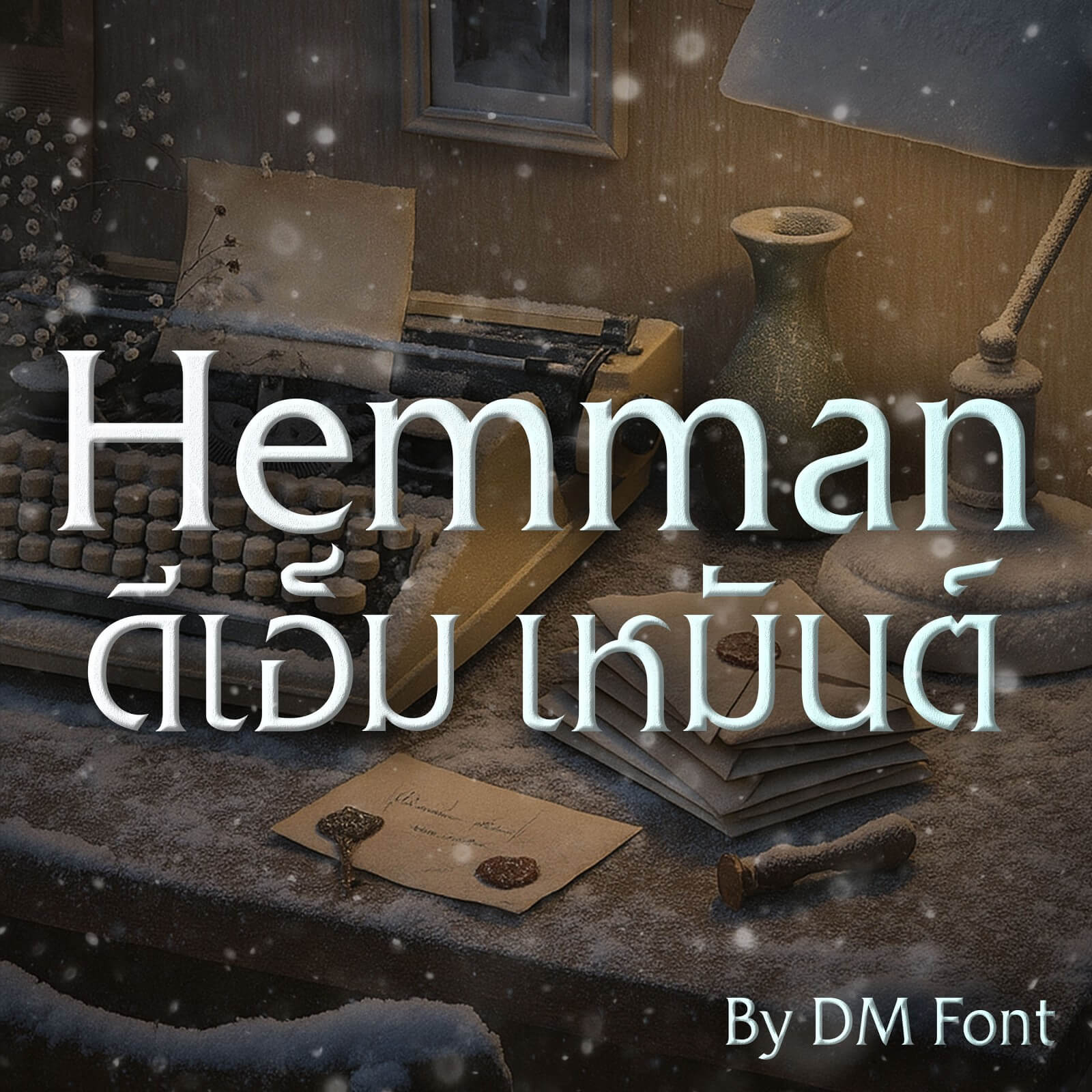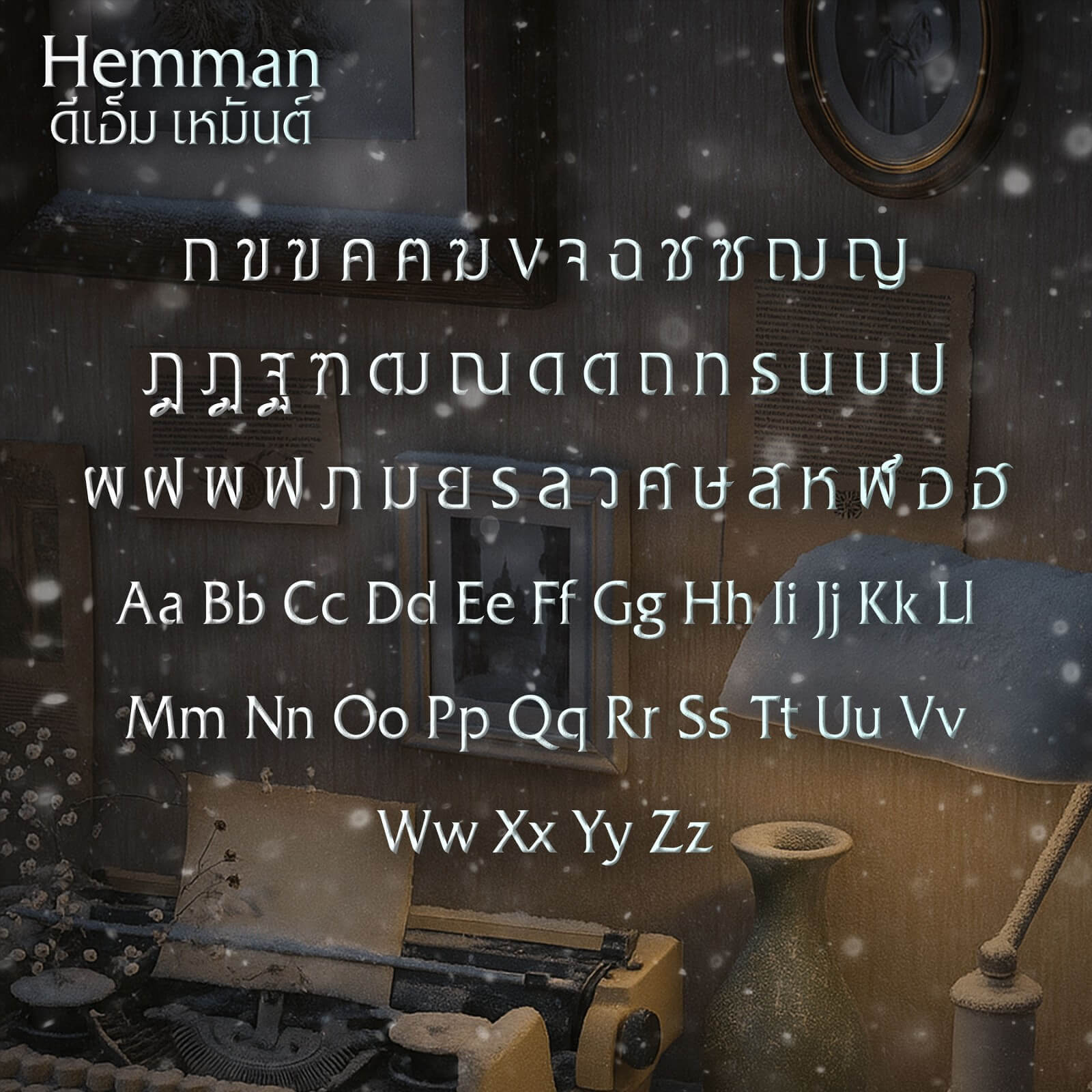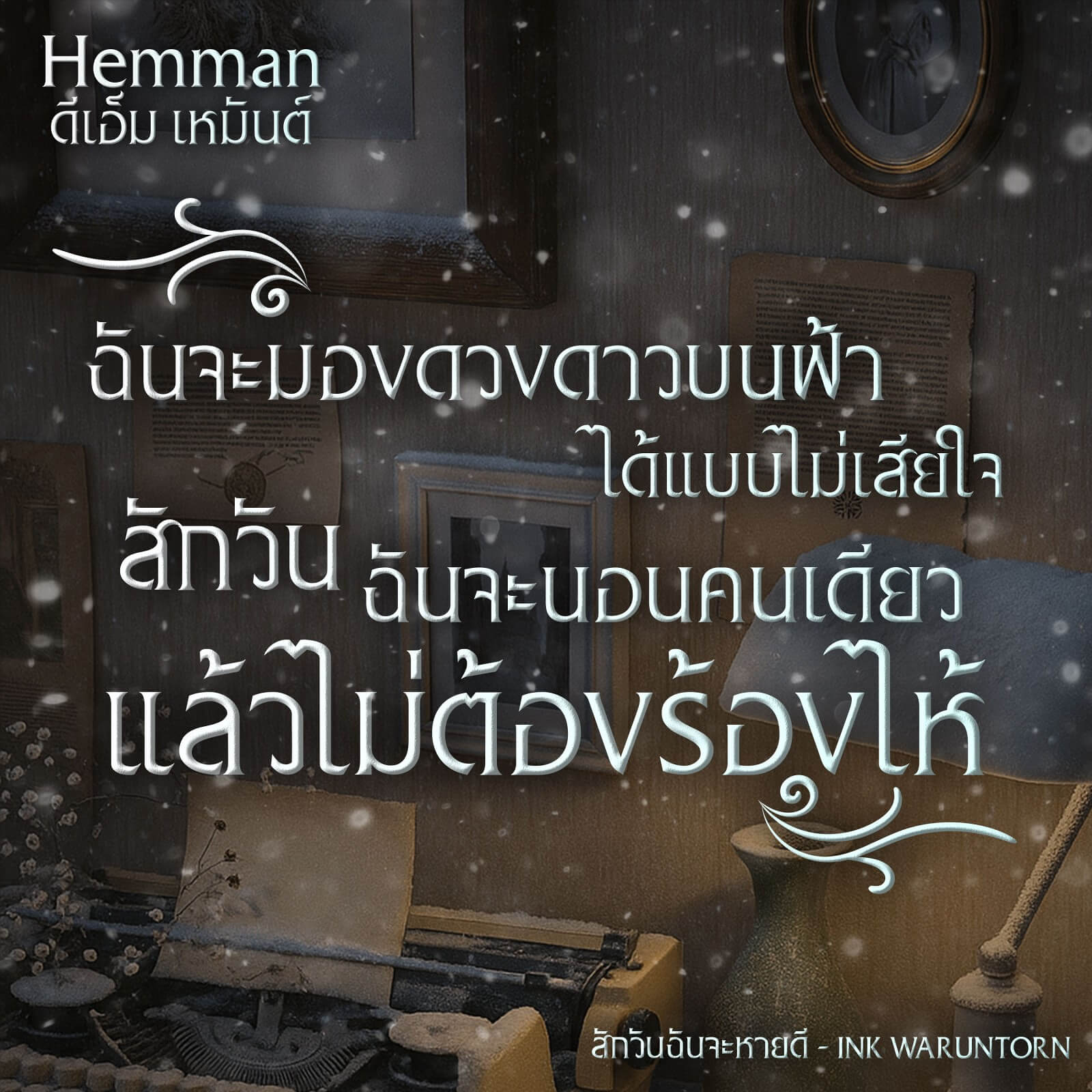
DM Hemman (ดีเอ็ม เหมันต์)
ตัวอักษรที่ออกแบบด้วยเส้นสายโค้งมนและจังหวะที่นุ่มนวล ถ่ายทอดความละมุนละไมอย่างมั่นใจ เหมาะกับงานออกแบบที่ต้องการความเรียบง่ายแต่เปี่ยมเสน่ห์ ไม่ว่าจะเป็นสิ่งพิมพ์ โปสเตอร์ บทกวี หรืองานสร้างสรรค์ที่อยากให้ผู้ชมรู้สึกอบอุ่นและน่าจดจำ